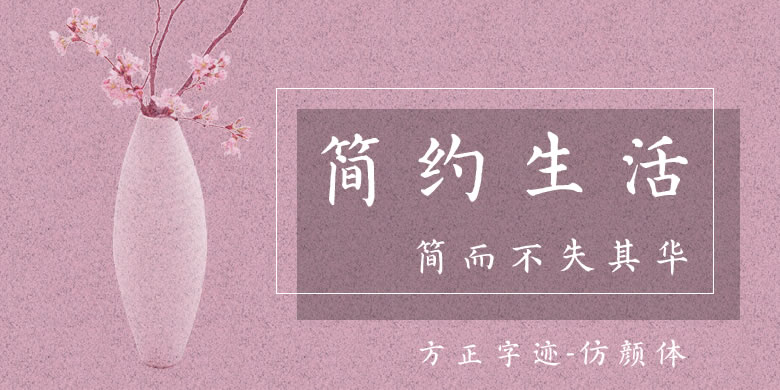
方正字迹-仿颜体
字体品牌: 方正字迹 设计师:杨国民 字体分类:楷书 字体属性:精品字 字符集:大陆简体(GB2312-80)、大陆繁体(GB12345-90) 发布时间: 2016
方正字迹-仿颜体既具备颜体的特点,又与颜体特意拉开距离。颜真卿中年时期,以“多宝塔”为代表的颜体字结构紧凑,骨力洞达;其晚年以“颜勤礼”为代表的颜体字中宫宽和,笔画绵里裹铁,肃穆古拙。颜体笔画厚重,一般只适用于标题,这款仿颜则减细了笔画,并弱化了横竖粗细的对比,使得它可以胜任中等字号的长文本。适用于文化类的宣传设计,以及商业类品牌的广告和产品包装设 计